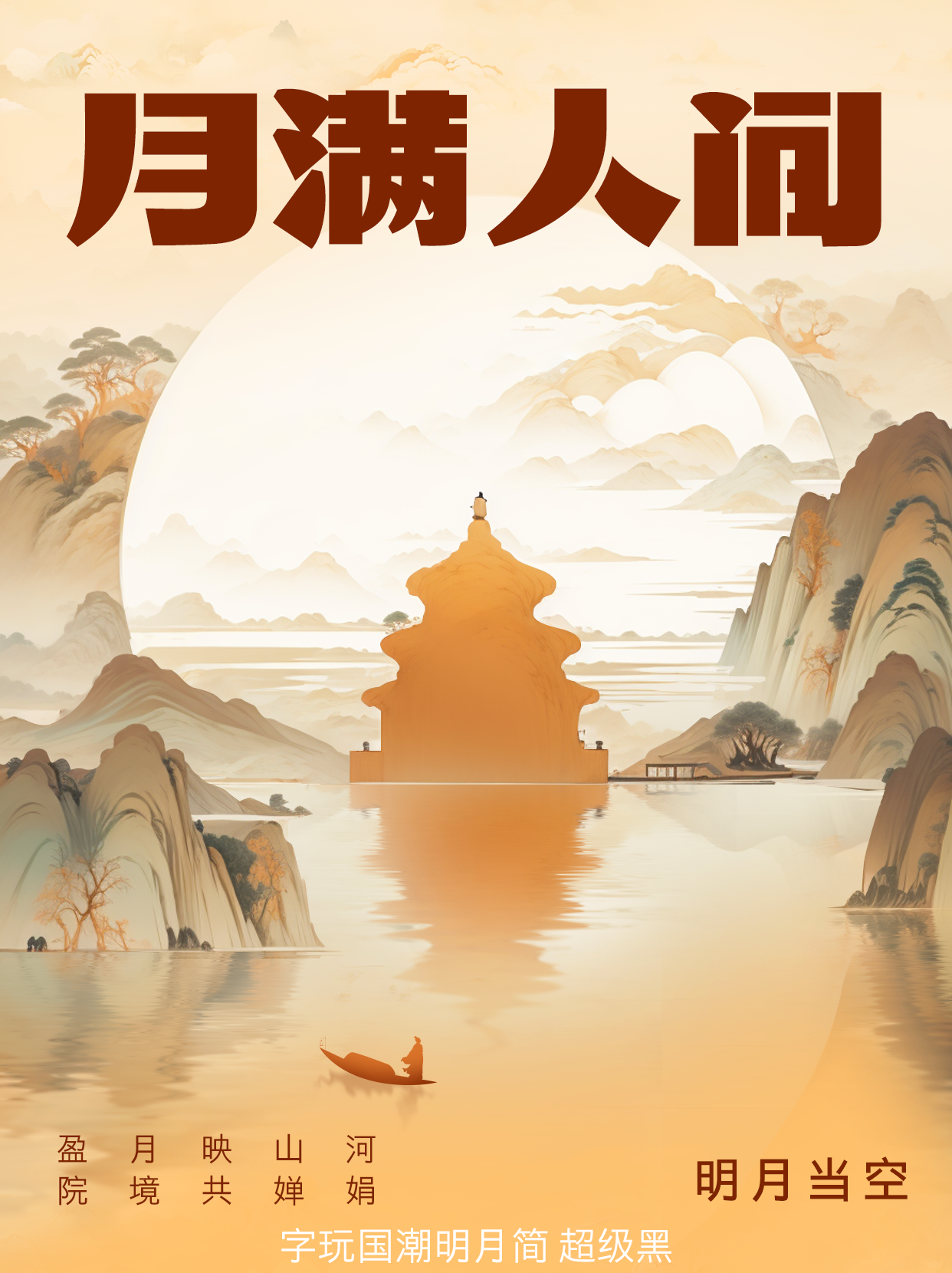
字玩国潮明月简 超级黑
字型整体宽扁规整,是一款布白均匀,中宫较大,重心平稳统一的宋黑字体。笔画简洁均匀,没有过多装饰,笔画横细竖粗,曲线流畅,其中“点”笔画起笔处和“撇”笔画收笔处加入自然的切口设计,撇捺笔画弧线流畅平滑,整体融入宋体笔画特点,“钩”笔画运用圆角简洁的设计。这款字在黑体简约柔和的同时带有宋体字的精致。结构稳重疏密均衡,简洁有力,字体显示醒目出色,适用场景广泛。